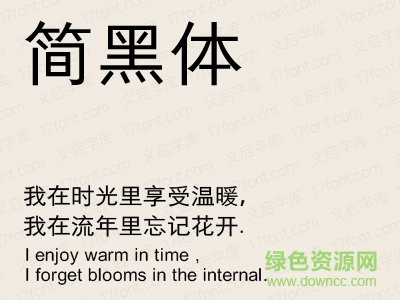
义启简黑体ttf免费版是一款简约干净的义启字体,该字体线条流畅,字形飘逸大方,印刷效果非常出色,喜欢的朋友快来绿色资源网下载吧!
义启简黑体字体介绍
简黑体,即简约而不简单,线条收笔处多以喇叭状收尾,结构经典内敛外扩重心微向上移,章法明朗流畅。 简黑体,端庄简约,笔画上处理精致得当。结构上分配块面合理,字与字间的距离分配阅读舒适爽朗。尤其在手机等移动小屏幕上显示更是简约极致的体现线条美。